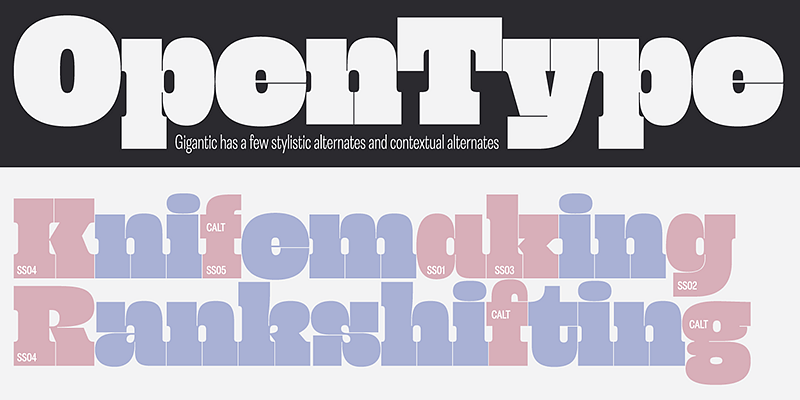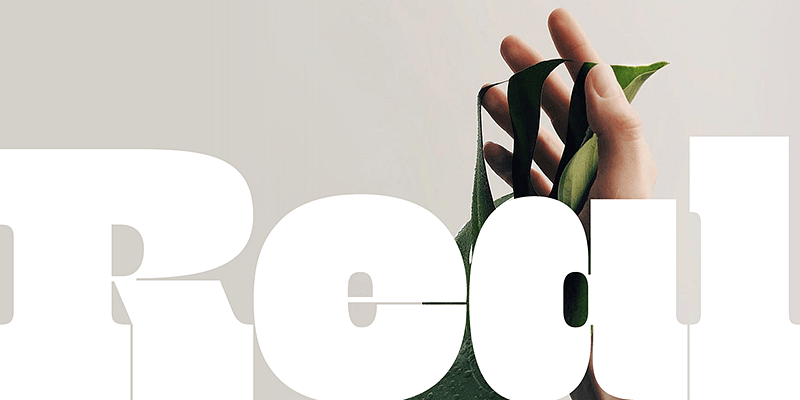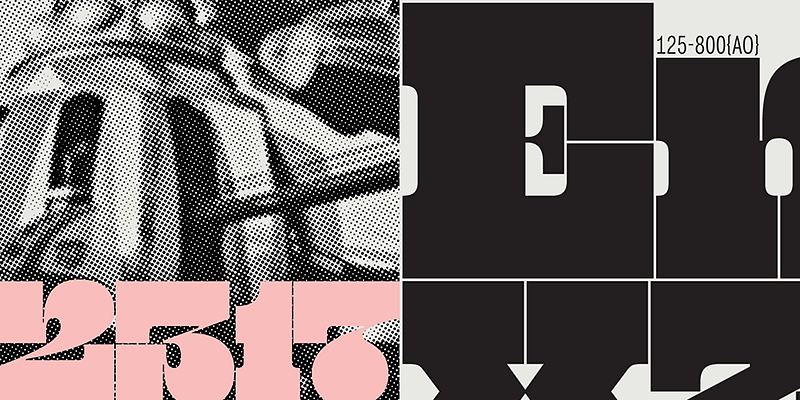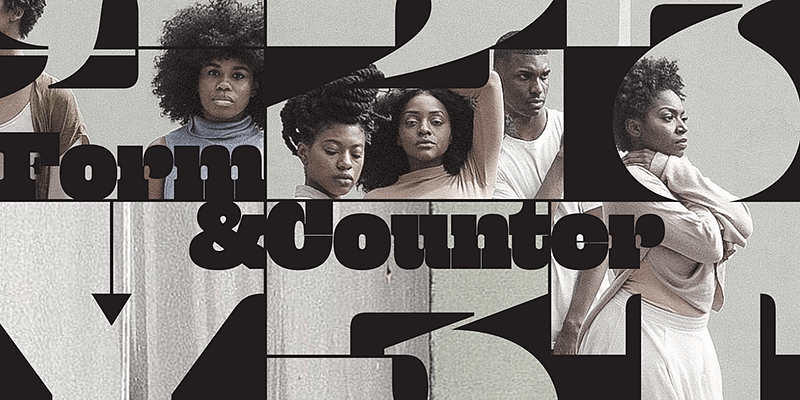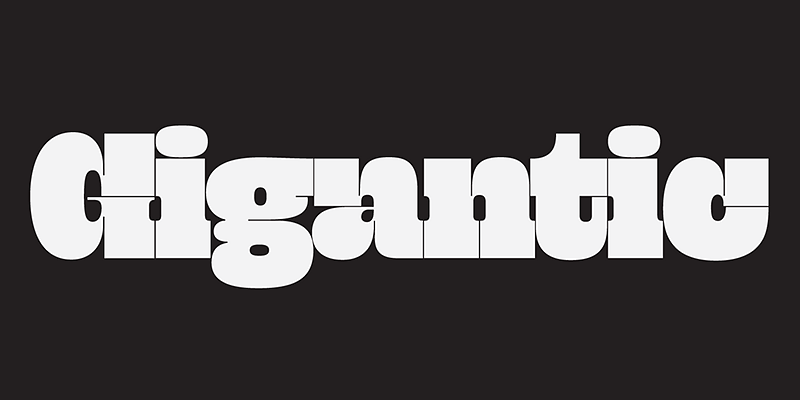
처음에는 Schizotype이었고, 그 다음에는 Eclectotype이었습니다. 이제 작품에 새로운 생명을 불어넣을 서체를 제작한 Dave Rowland Type을 만나보세요. 글꼴에 대한 열정으로 Dave는 예술성과 기술을 사용하여 매혹적인 서체 배열로 단어를 변화시킵니다. 단순한 글자 그 이상으로, 그의 글꼴은 눈에 띄게 다재다능하고 매우 세밀하며 세심하게 세련되었습니다. 클래식 세리프체, 현대적인 산세리프체, 유쾌한 스크립트 또는 기발한 디스플레이가 필요할 때 Dave Rowland Type은 감정과 스타일, 스토리텔링을 구현할 수 있습니다.